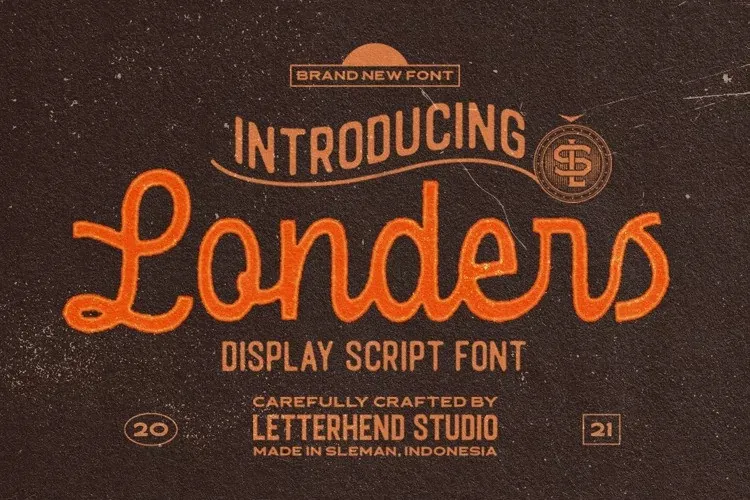
A fonte ‘Londers Font’ é uma tipografia script robusta e assertiva criada pelo designer Letterhend. Com linhas arredondadas e curvas suaves, ela oferece um toque vintage único perfeito para a criação de marcas e logotipos. Suas formas fluidas e elegantes são projetadas especificamente para uso em títulos, rótulos, carteirinhas, embalagens, cartões de casamento ou até mesmo revistas e livros – oferecendo um toque atraente em qualquer tipo de conteúdo gráfico formal. A ‘Londers Font’ é uma escolha perfeita para quem busca dar um toque distintivo às suas criações digitais. É o que você precisa para se destacar na web ou no seu próximo projeto visual.